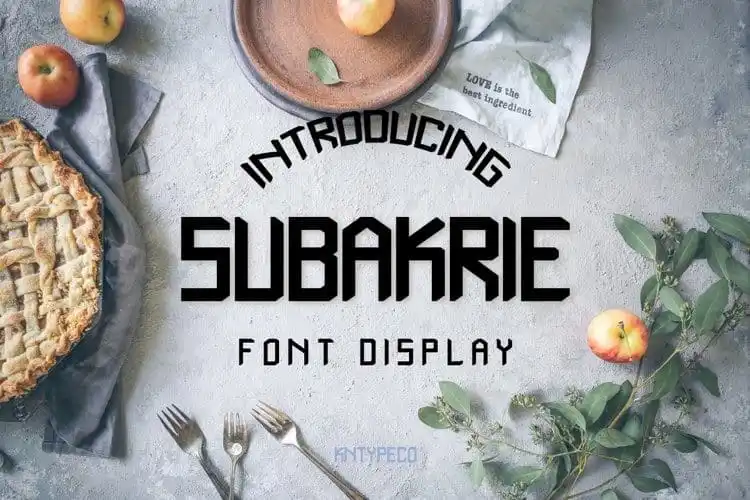
A Subakrie Display Font é uma escolha perfeita para quem busca dar vida aos seus projetos criativos com estilo. Com letras maiúsculas, números e alguns sinais de pontuação, esta fonte fornece um toque vintage e moderno num mesmo momento. Fabricada pela kntypeco, essa tipografia bold é ideal tanto para aplicar em desenhos gráficos quanto em design web. Adicione a Subakrie à sua lista de recursos e observe como ela transforma suas idéias criativas em algo realmente vívido. Esta fonte de exibição tem tudo o que você precisa para tornar seus projetos ainda mais expressivos.